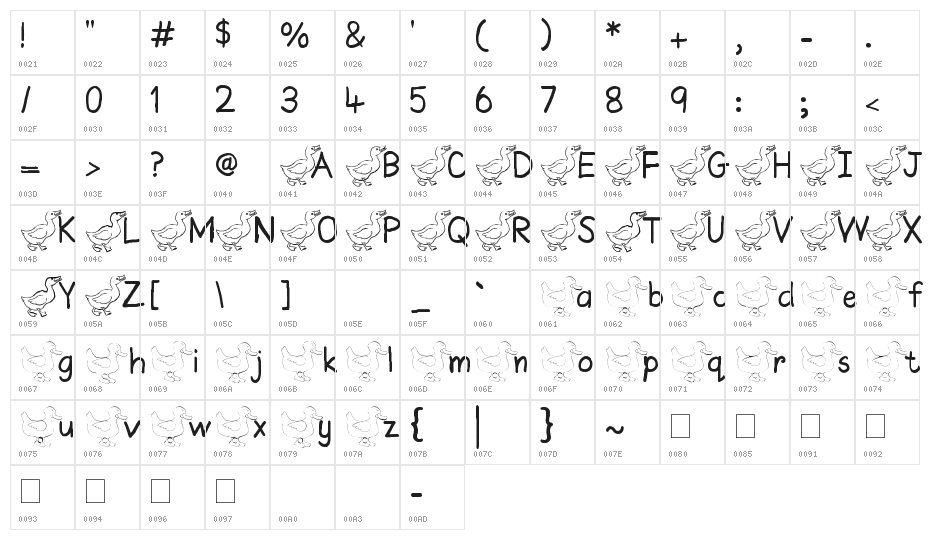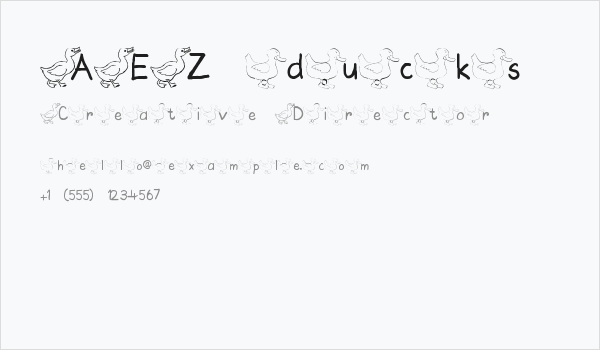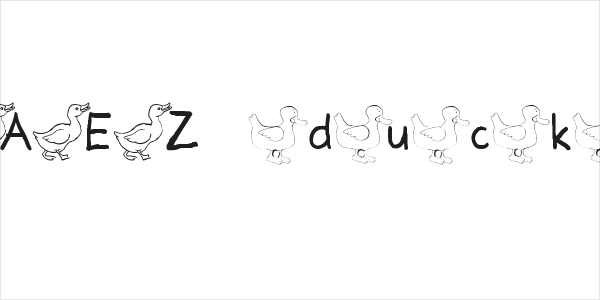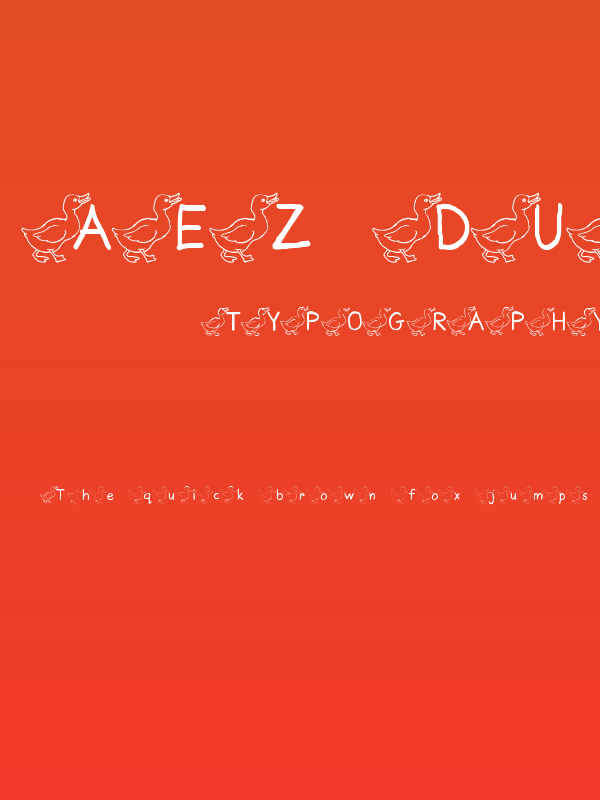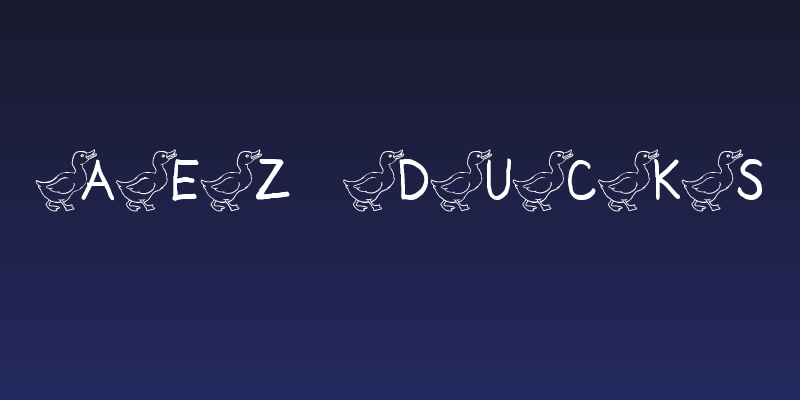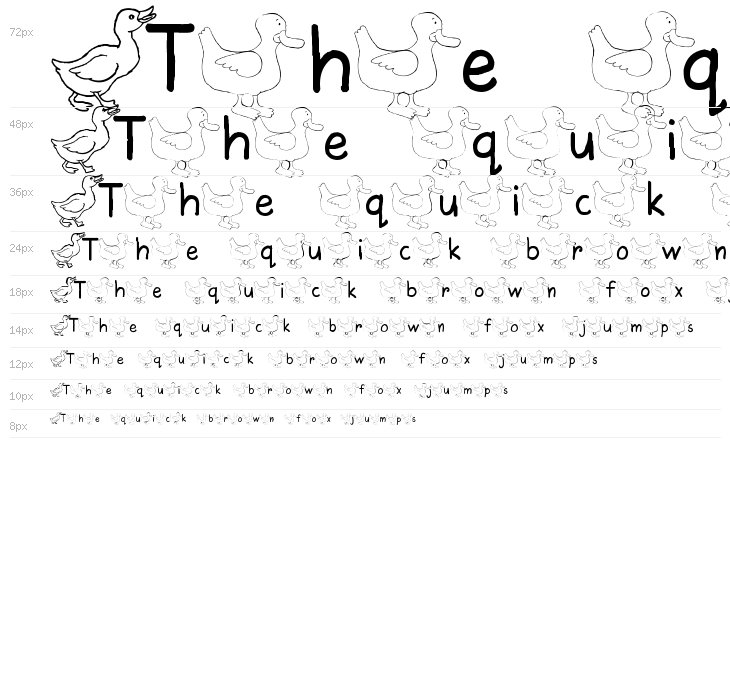
AEZ ducks Font
| Anwendungsfall | Headlines, Logos, Creative projects |
| Vorgeschlagene Projekte | Ideal for children's books, playful branding, greeting cards, and any project needing a fun and whimsical touch. |